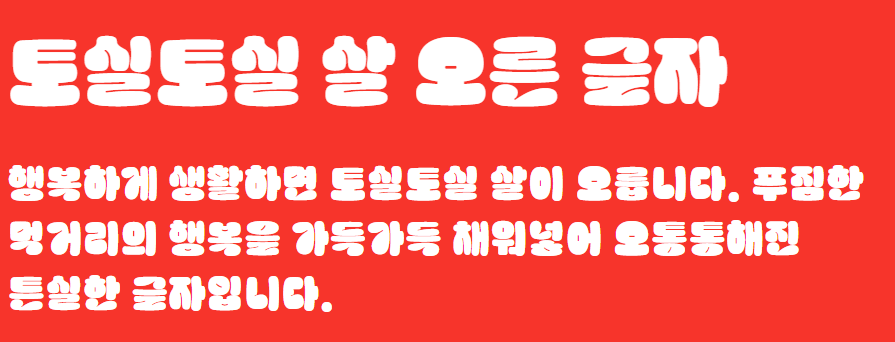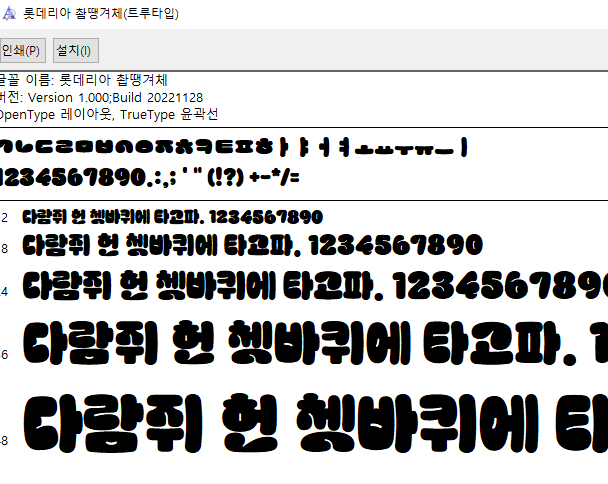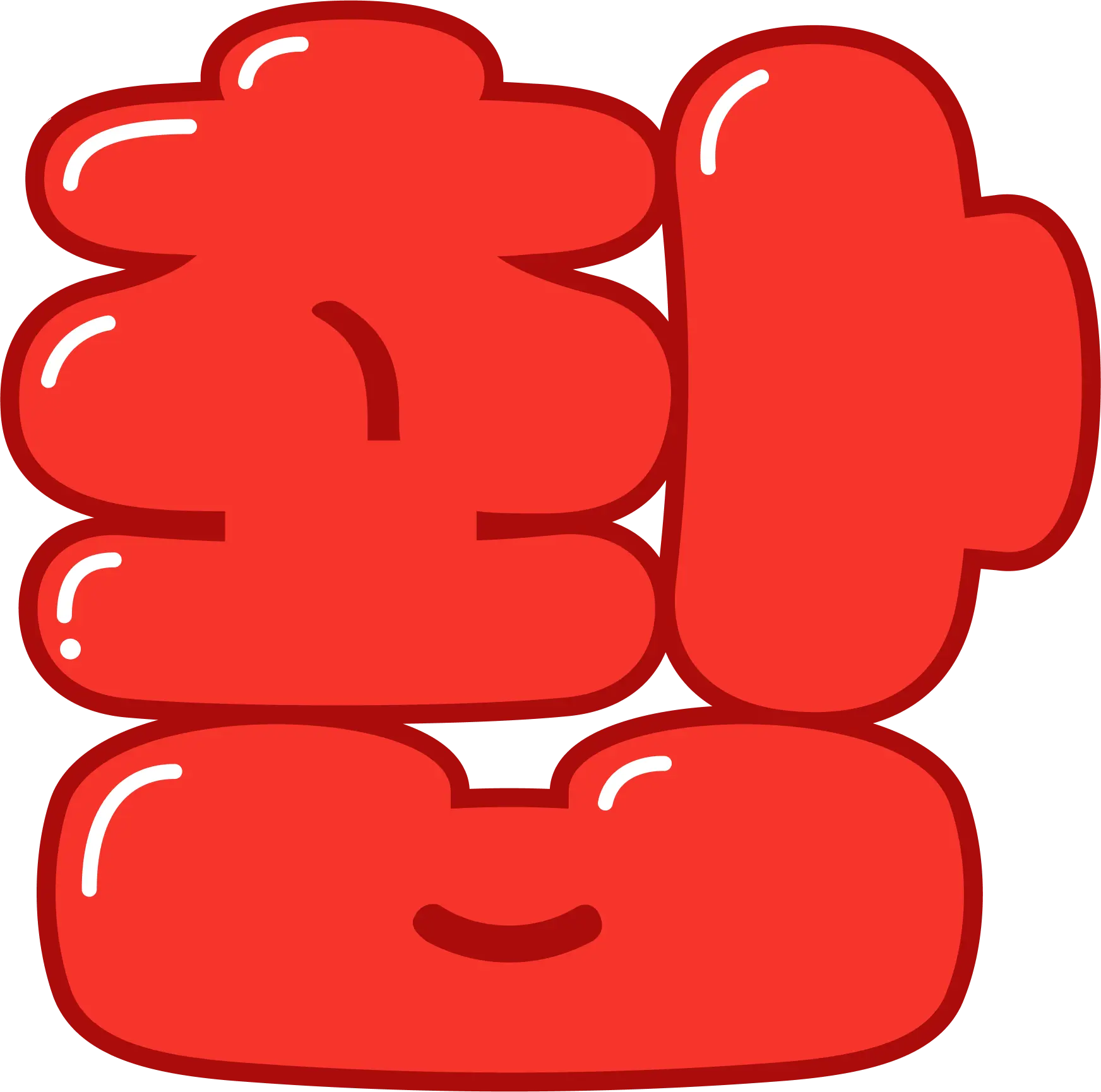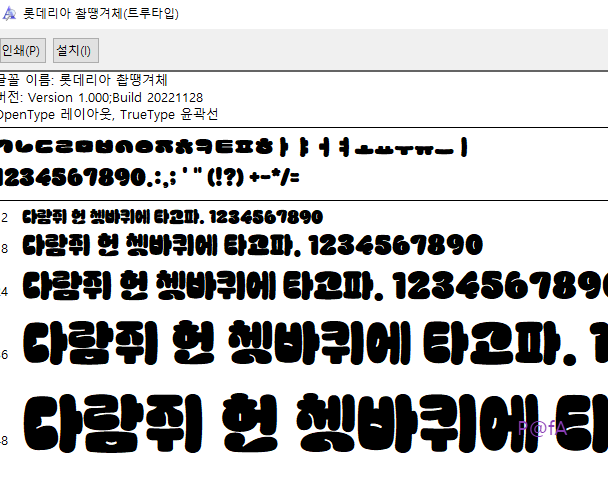
롯데리아에서 제작한 시선을 사로잡는 색다른 폰트인 롯데리아 촵땡겨체를 무료로 다운로드하는 방법을 살펴본다. 더불어 누구나 무료로 사용이 가능한 롯데리아 촵땡겨체를 윈도우에 설치하는 방법과 코딩 시에 사용하는 방법도 살펴본다.
시선을 사로잡는 색다른 폰트 롯데리아 촵땡겨체 무료 다운로드
상기 이미지에서 보듯이 롯데리아 촵땡겨체는 촵이란 글자에서 느껴지듯이 토실토실 살이 오른 듯한 형태로 아기 팔뚝 같이 시선을 확 사로잡는 색다른 폰트로 어그로용으로 제격이다.